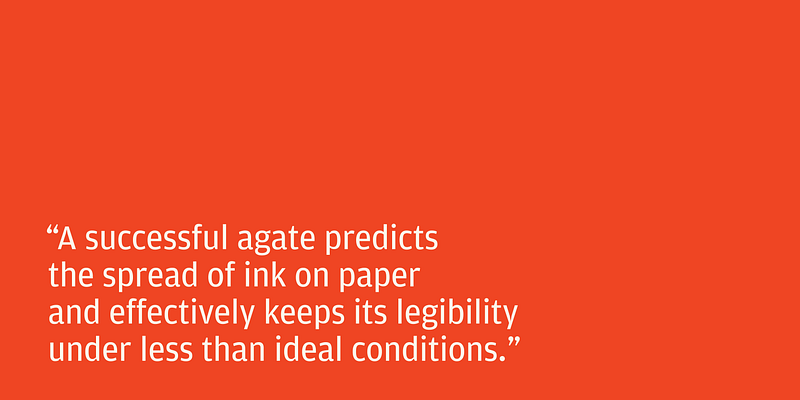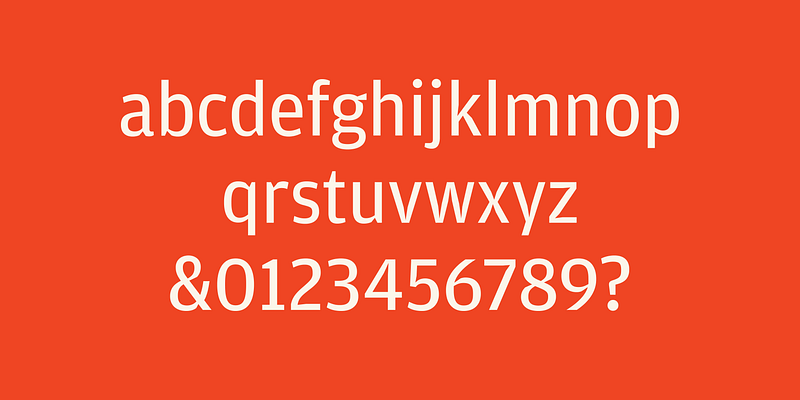
Un style agate qui fonctionne prédit la propagation de l’encre sur le papier et conserve efficacement sa lisibilité dans des conditions difficiles. Fasciné par les aspects visuels de ces compensations entièrement fonctionnelles, Christian Schwartz a conçu Amplitude, une vaste série sans empattement pour le texte et l’affichage qui transforme la fonction en style : des coupes à angle profond assurent la lisibilité des petites tailles, tout en ajoutant du caractère aux tailles d’affichage. FB 2003